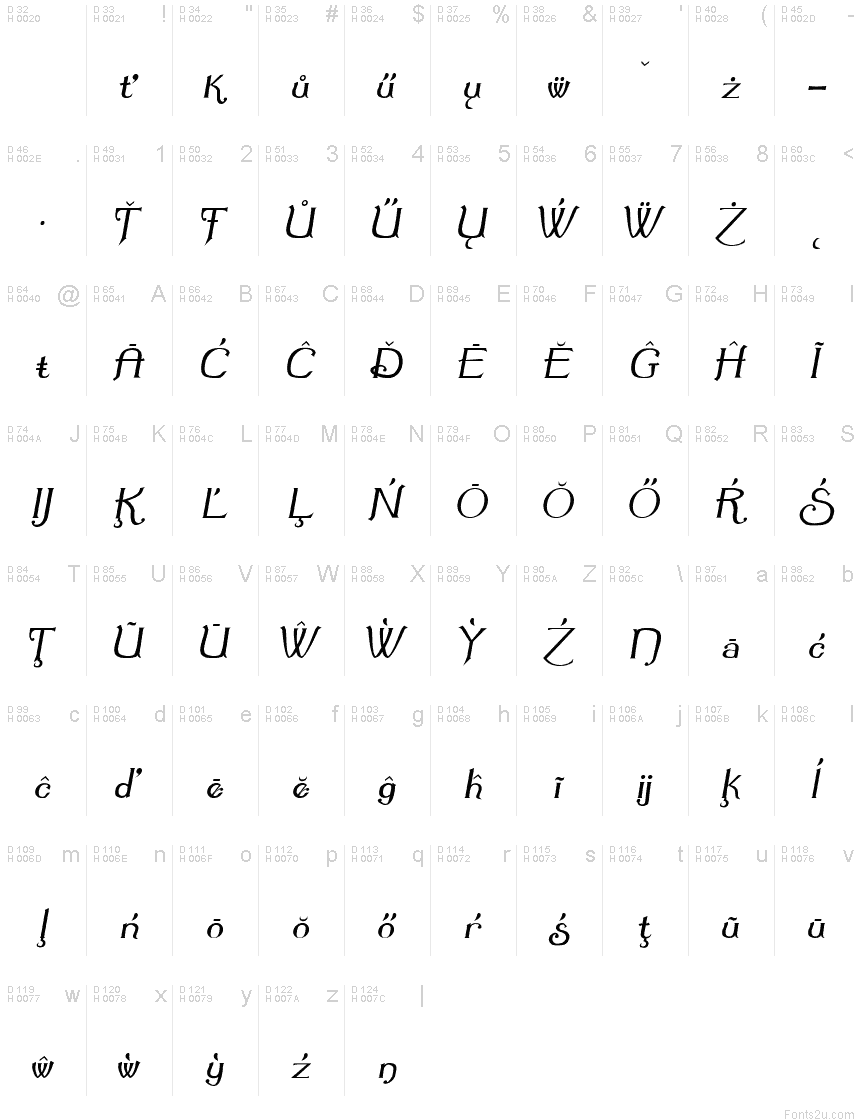
Summertime Extra Oblique
Summertime Extra Oblique by Sara to bezpłatny kaligraficzny font typu display o subtelnym klimacie Art Nouveau. Litery łączą w sobie smukłe, kontrastowe pociągnięcia z wijącymi się ozdobnikami i zaokrąglonymi akcentami, co nadaje całości swobodny, ornamentalny rytm, bardziej przypominający pismo odręczne niż klasyczną antykwę.
Sprawdzi się w butikowym brandingu, menu kawiarnianych, na okładkach książek, zaproszeniach i nagłówkach czasopism, gdzie odrobina dynamiki dodaje słowom elegancji. Ten darmowy font najlepiej prezentuje się w krótkich tekstach, na kartach tytułowych i w monogramach, ponieważ jego zamaszyste krzywe i detale w kształcie kropel potrzebują przestrzeni, aby w pełni wybrzmieć.